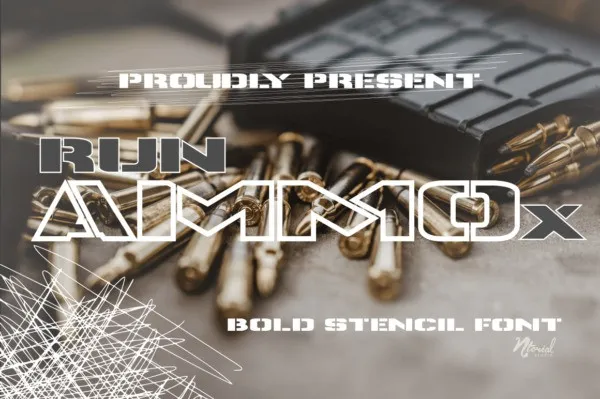
A Runammox Font é uma opção única para designers que procuram um estilo forte e moderno. Esta tipografia exibida foi projetada pelo NtorialStudio inspirada no design tradicional e robusto dos estêncis militares vintage. Sujeitado a cuidados meticulosos, esta fonte se adequa perfeitamente às necessidades de seus designs relacionadas aos temas do exército, esportes e outros. Com sua beleza única e versatilidade em diferentes formatos, ela é ideal para criações como roupas, logotipos, identificações visuais, cartazes e muito mais. Engajante e atemporal, a Runammox Font oferece uma variedade de opções para personalizar sua arte digital.